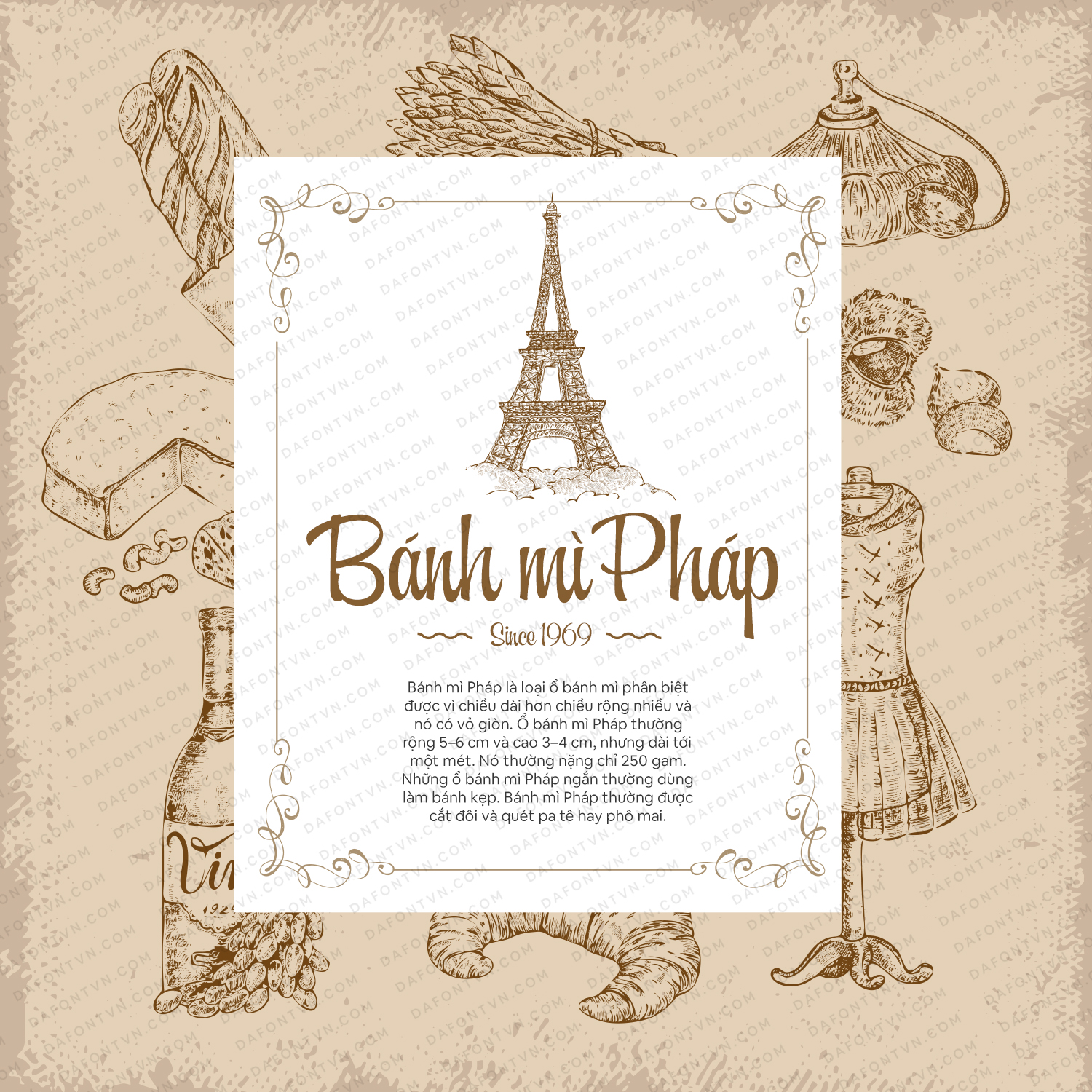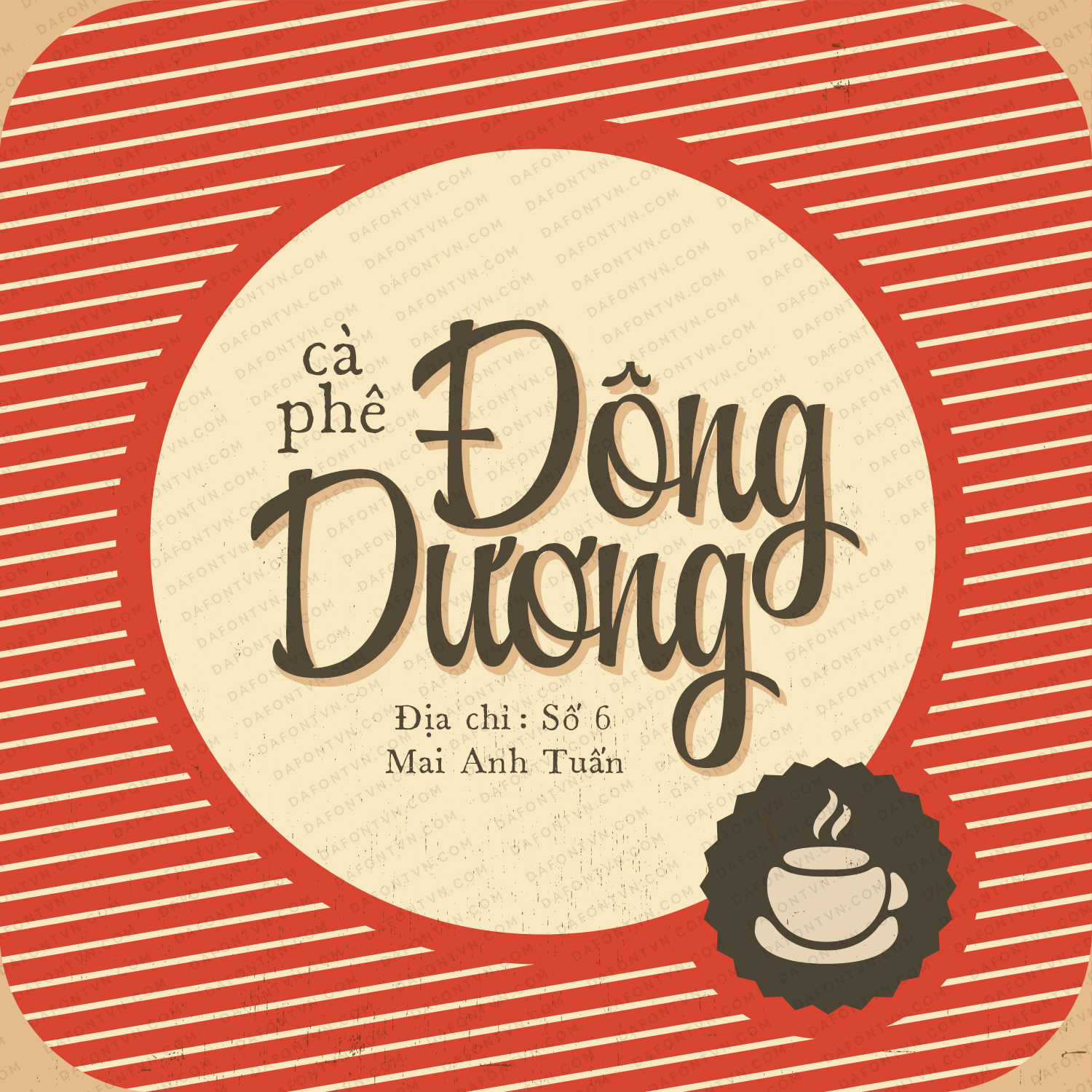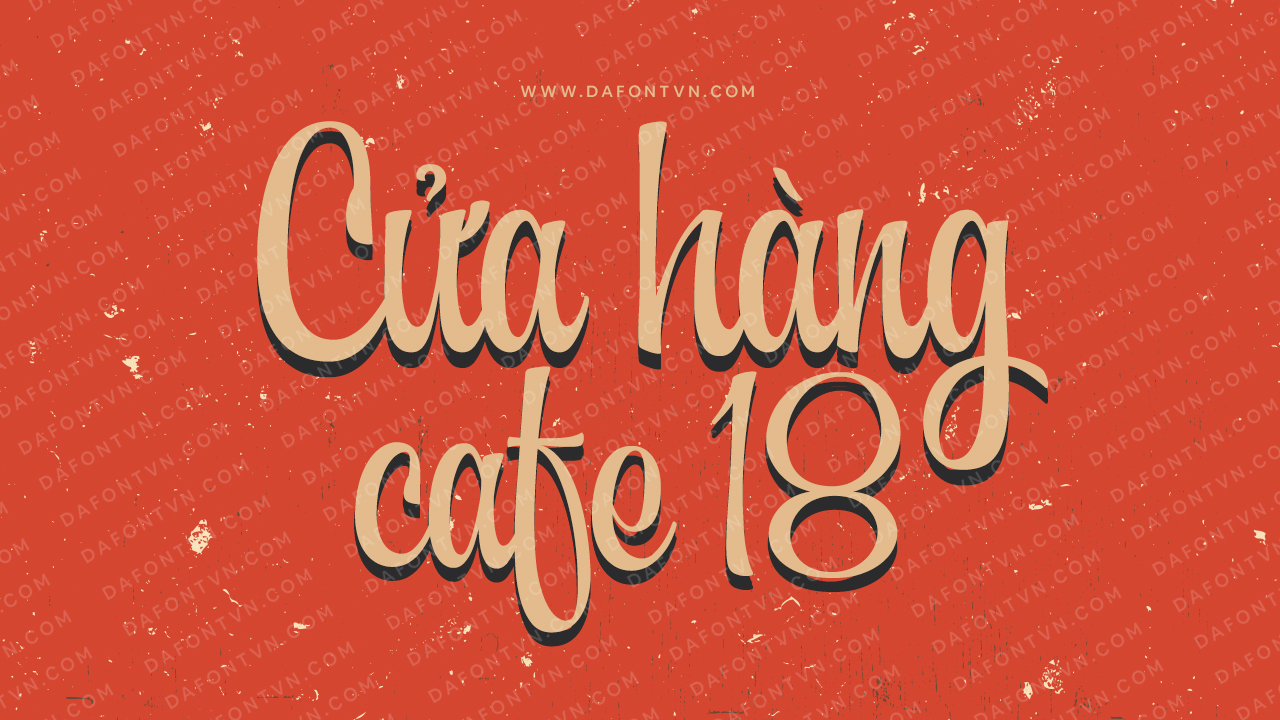
Creation là một script font có kiểu chữ thẳng đứng trông khỏe khoắn, cổ điển và có sức hấp dẫn khi nhìn vào. Mỗi hình dạng chữ cái đã dược thiết kế để có một ký tự dễ dàng ghi nhớ trong đầu.
Creation này có các ký tự cổ điển, những đường nét rõ ràng và những đường cong mượt mà mang đến cho bất kỳ dự án thiết kế nào một nét chữ đẹp mắt.
Kiểu chữ này hoàn hảo khi sử dụng ở kích thước lớn chẳng hạn như trong bố cục tạp chí, bao bì, sách, thiết kế tiêu đề, thương hiệu thời trang, quần áo, thiết kế trích dẫn và nhiều thiết kế khác.